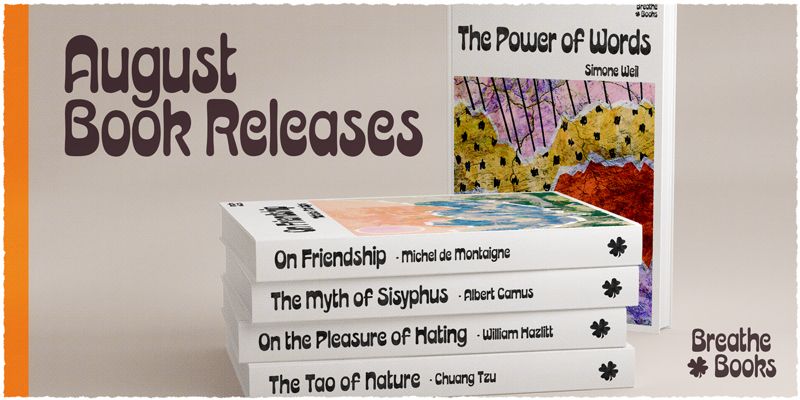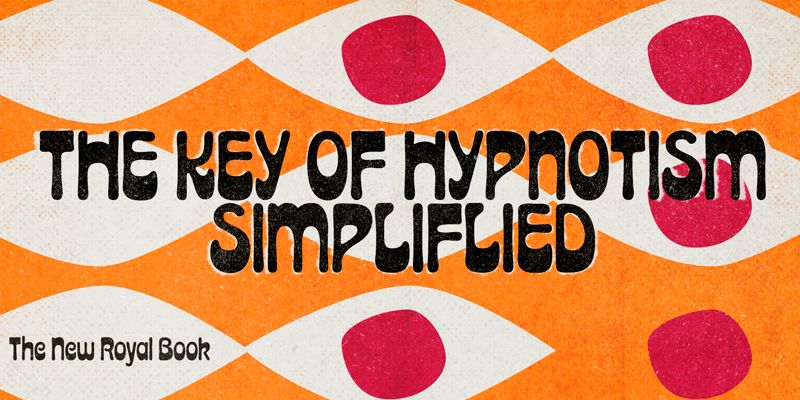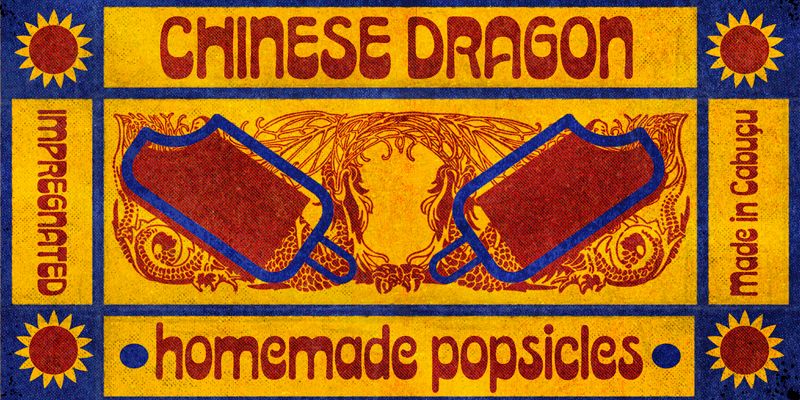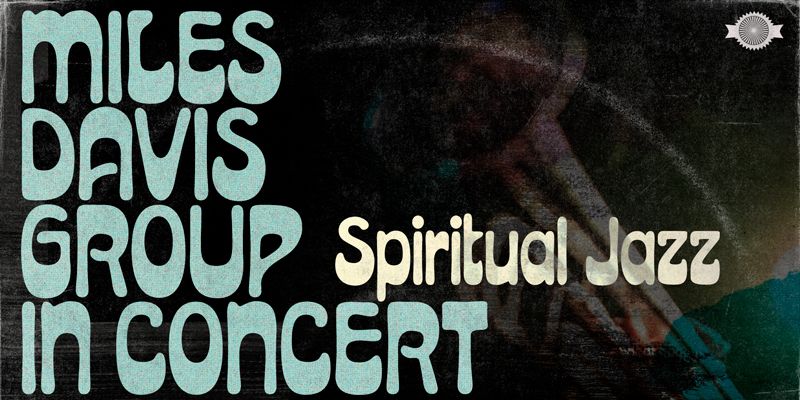
Acid Green ist eine Display-Schriftart mit psychedelischem Flair. Ihre Wurzeln gehen auf ein 1914 von J. M. Bergling, einem Schmuckgraveur und Schriftdesigner, entworfenes Alphabet zurück, dessen Name unbekannt ist. Berglings Bücher über dekorative Schriften beeinflussten zahlreiche Künstler, darunter Vertreter des Jugendstils und des Art Déco. Sie eignet sich hervorragend für Display-Anwendungen im Retro-Stil oder mit psychedelischen Buchstaben. Acid Green bietet einen umfangreichen Zeichensatz und stilistische Alternativen für das gewisse Extra.